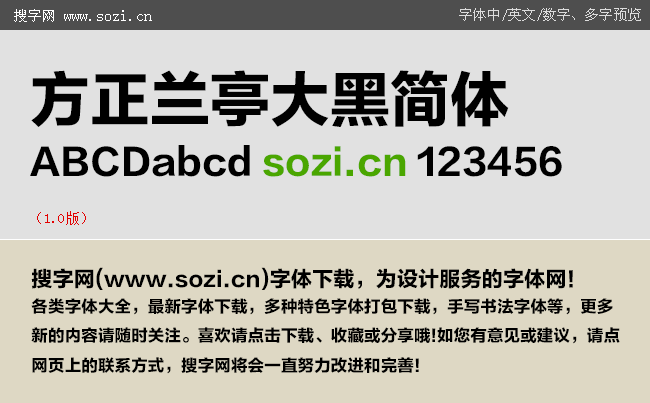
方正蘭亭大黑簡(jiǎn)體(FZLTDHJW)
搜字網(wǎng)提供一款方正蘭亭大黑簡(jiǎn)體中文字體下載,方正蘭亭大黑簡(jiǎn)體是一款非常厚實(shí)的中文字體,該字體端正醒目,線條粗曠,常用于報(bào)刊雜志排版,也適用于平面廣告,圖書印刷等廣告設(shè)計(jì)場(chǎng)合使用。